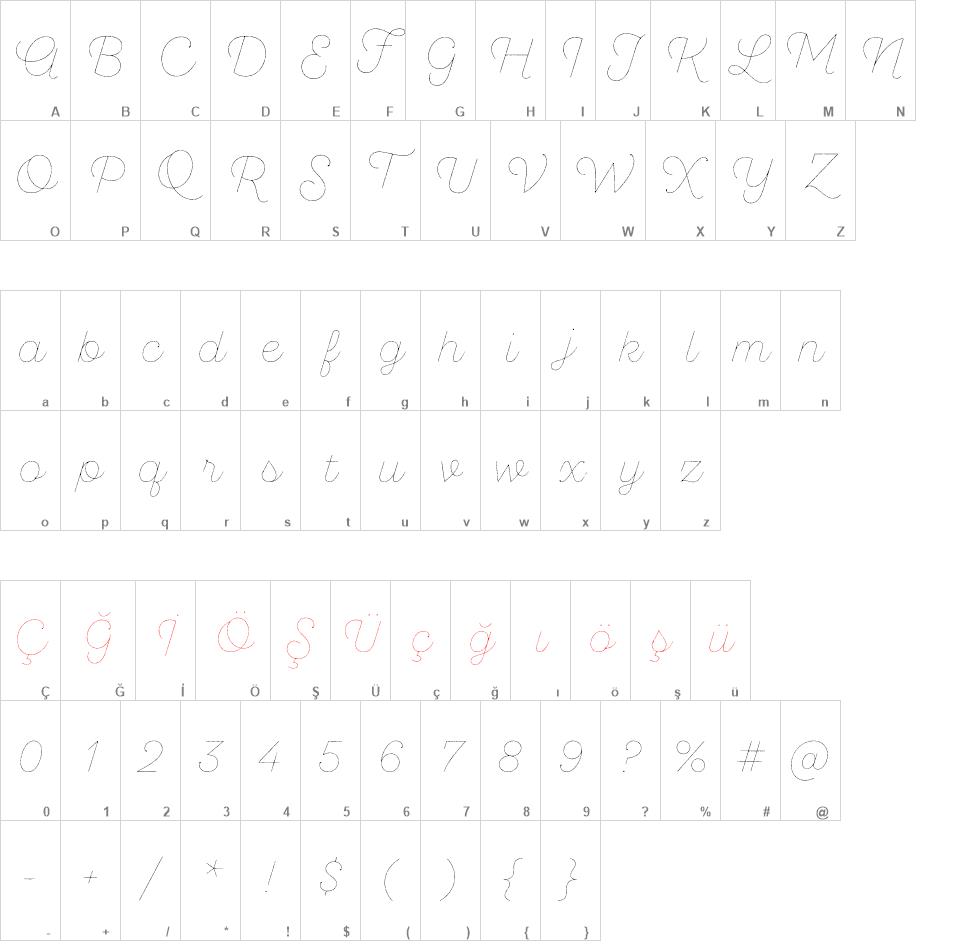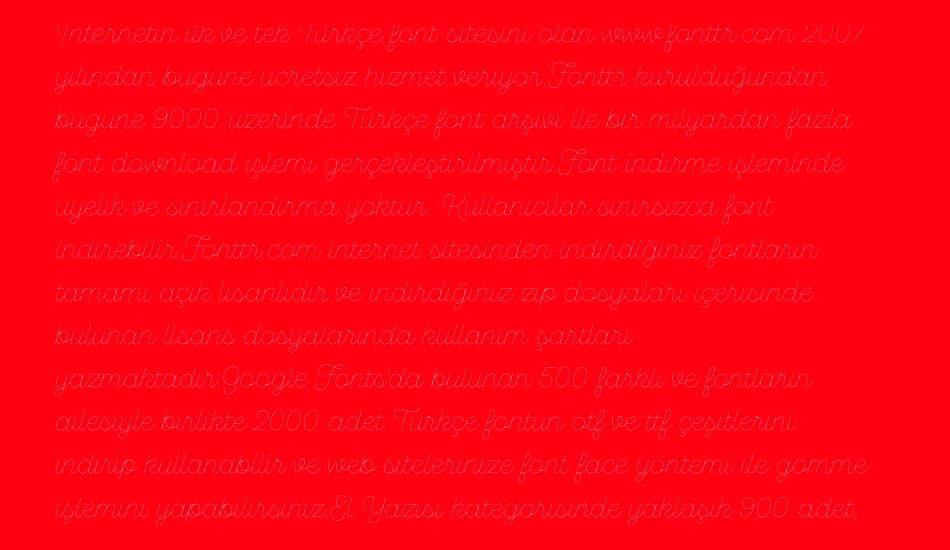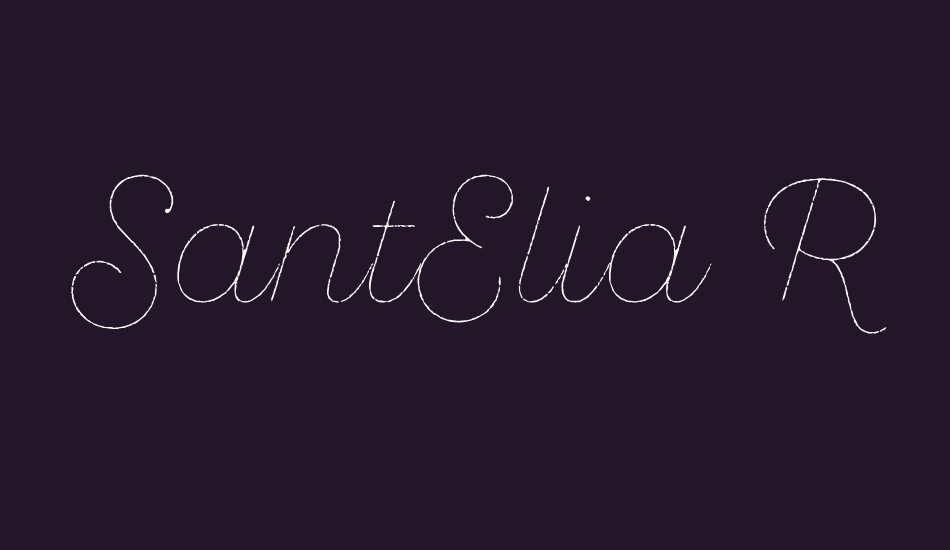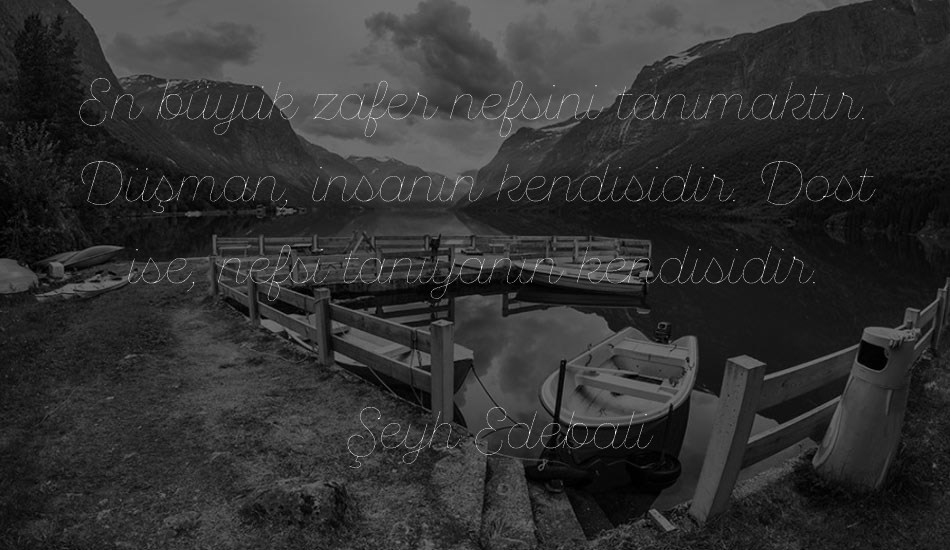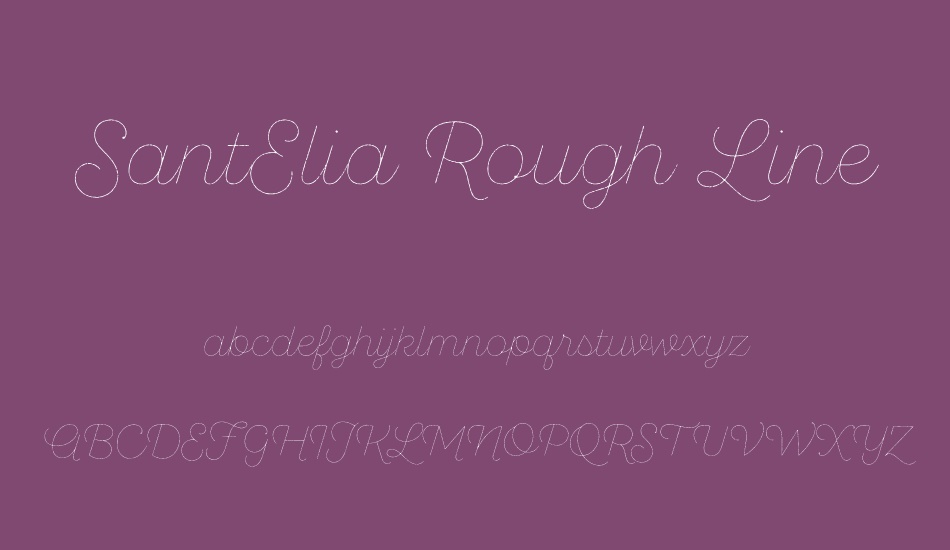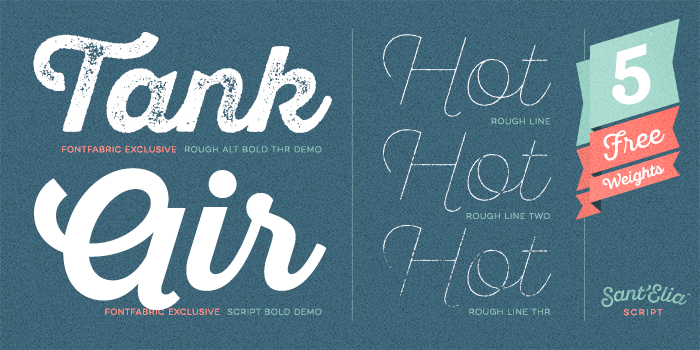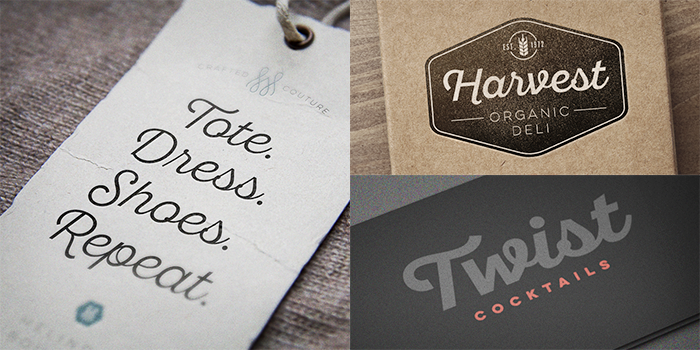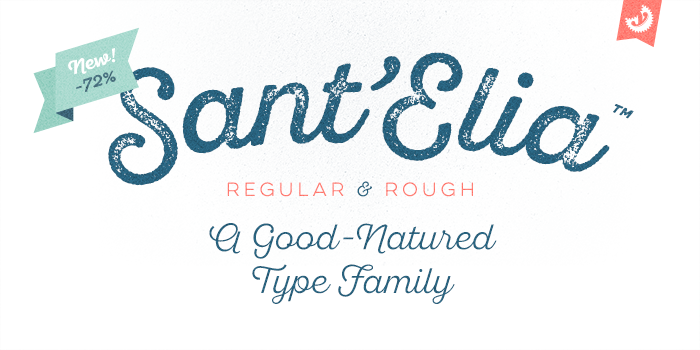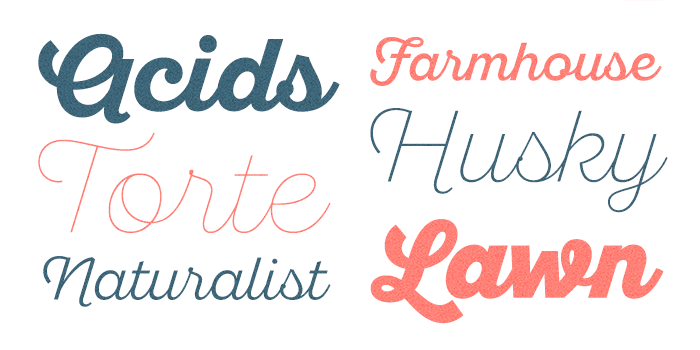
Sant’Elia Script font
Sarı Tasarım Stüdyosu'ndan Sant'Elia Senaryo, altı ağırlığa sahip düzenli ve kaba sürümleri olan sağlam modern bir ailenizdir. Formları gevrek ve karşılama ve canlılık sergiliyor. Alternatif sürümler ekstra enerji enjekte eden eğik vuruşlara sahiptir. Kaba ağırlıklar ek kontrol ve kişiselleştirme için karıştırılabilen üç farklı tehlike seviyesi içerir. Sant'Elia Rough Line, Line Two ve Line Three'ü ücretsiz deneyin!
SantElia Rough Line font